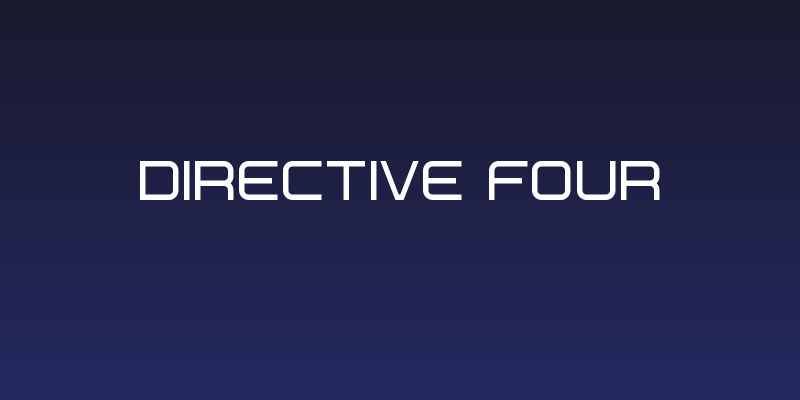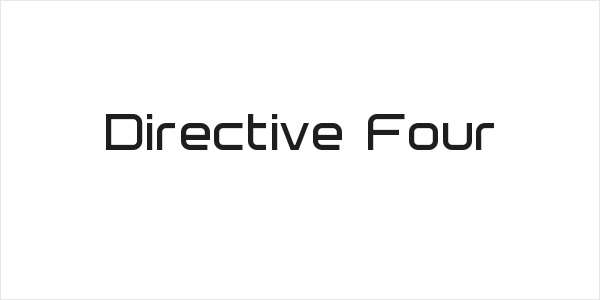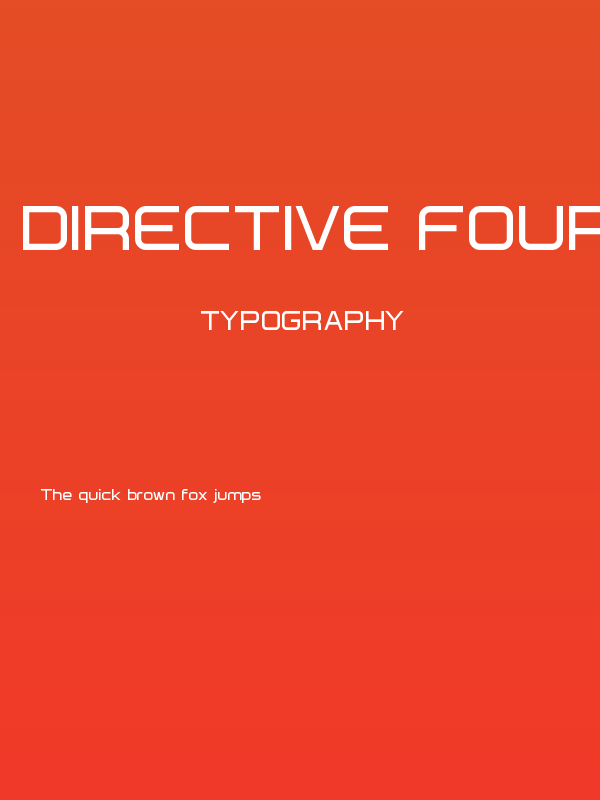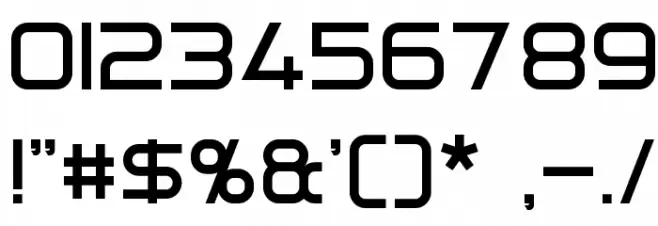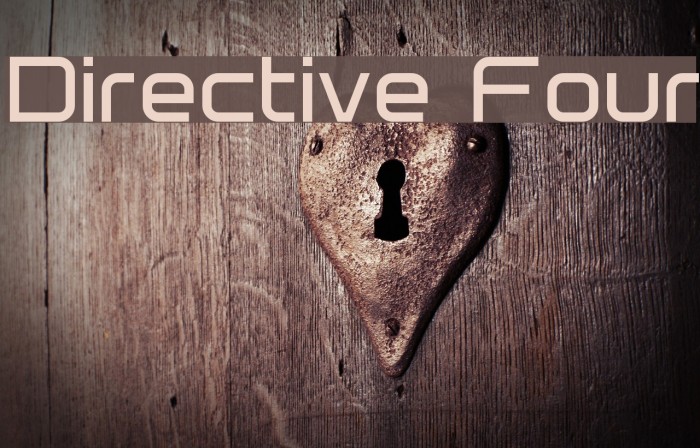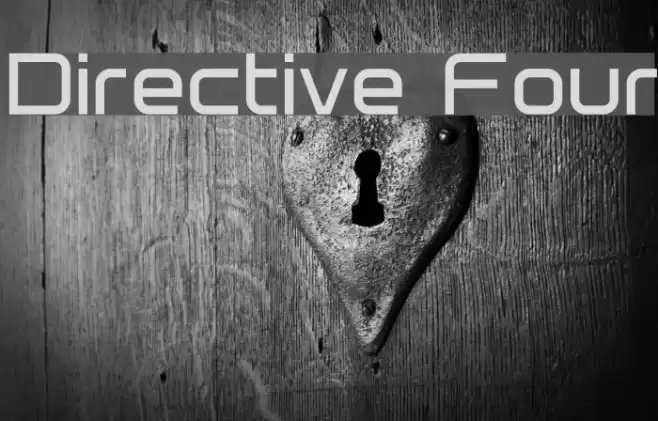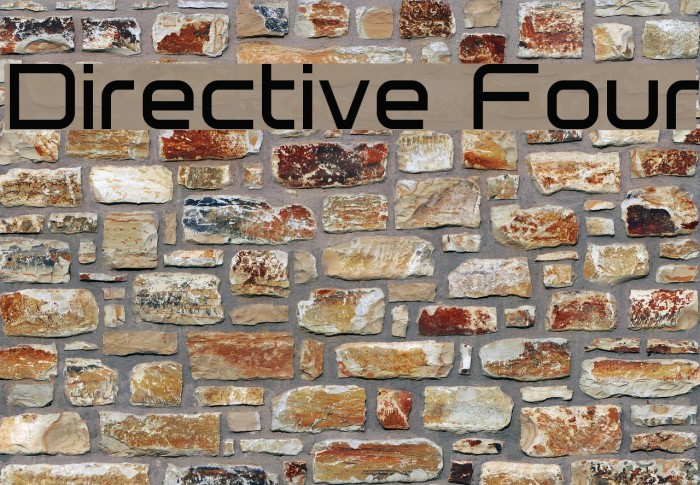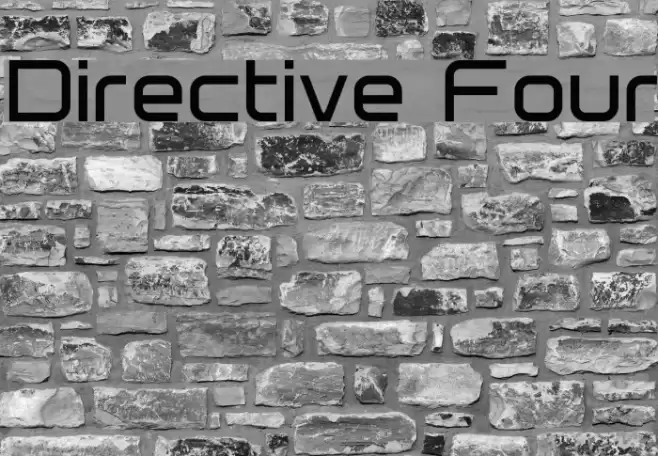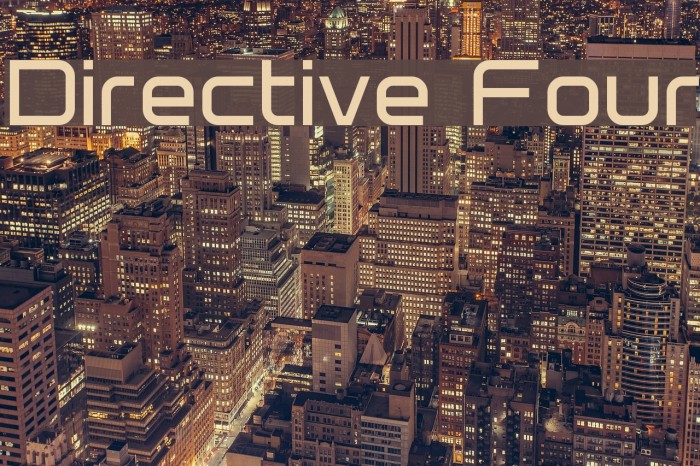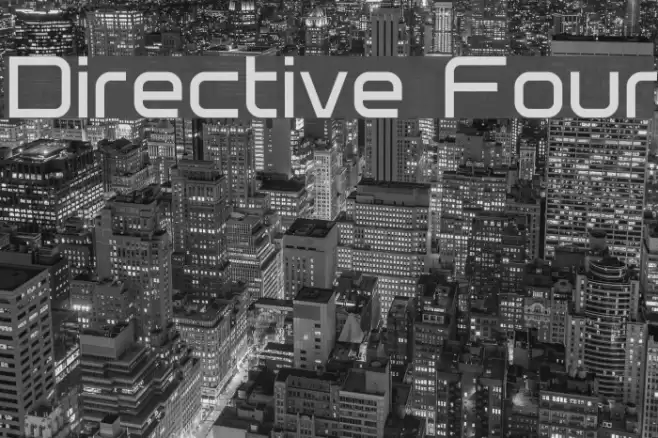
Directive Four Font
| 用途 | Headlines, Logos, Digital Interfaces |
| おすすめプロジェクト | Ideal for tech branding, digital interfaces, modern advertising, and minimalist design projects. |
| 作者 | Fonts by Dieter Steffmann |